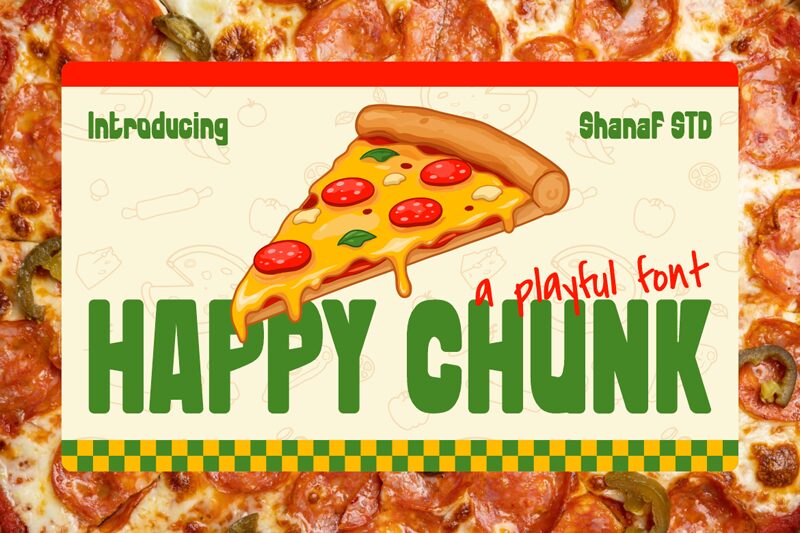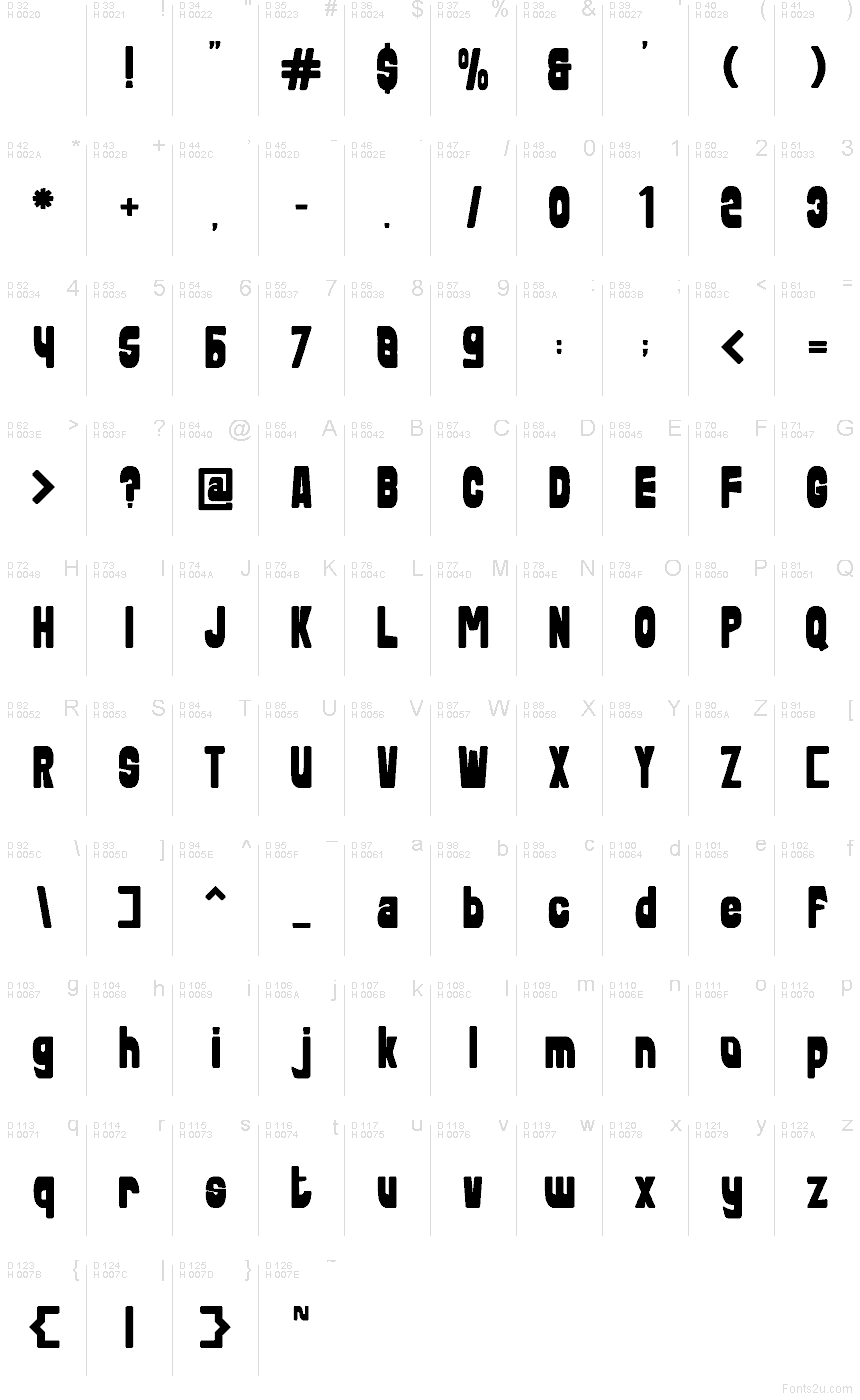
Happy Chunk de Putracetol Studio es una tipografía display tipo cartoon gratuita con trazos suaves e inflados, ideal para diseños divertidos y llenos de vida. Las letras son gruesas y dinámicas, con esquinas redondeadas, formas contundentes y un toque artesanal que le aporta mucha personalidad sin perder frescura.
Es perfecta para empaques infantiles, branding de dulces, invitaciones, stickers y redes sociales, donde una tipografía gratuita con tanto cuerpo puede sostener un mensaje por sí sola. Úsala en títulos, tarjetas o logotipos cuando busques un estilo suave y alegre en lugar de algo serio o formal.